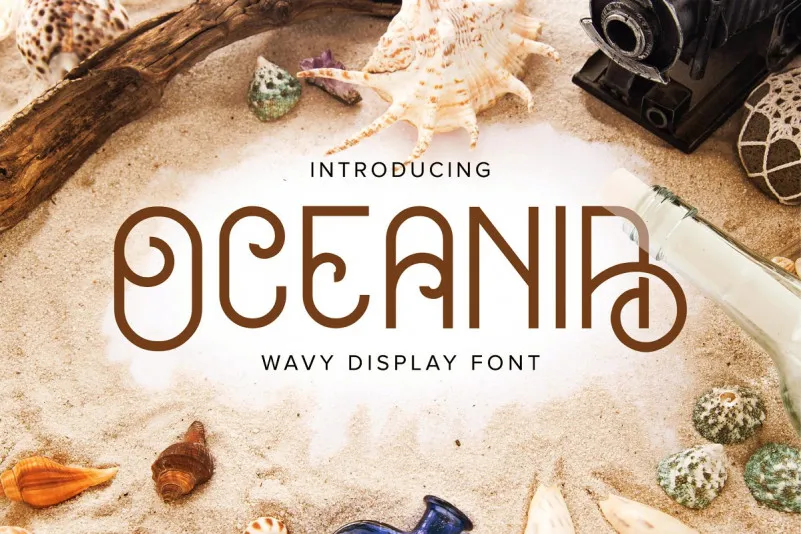
Oceania Display Font – Download Grátis
Descubra Oceania Display Font, uma fonte display icônica criada pela LetterStuff Typefoundry. Esta wavy typeface é perfeita para estilos visuais vibrantes e criativos. Com sua elegante onda doce e suave como o mar tropical, ela destaca-se em qualquer projeto de design. Ideal tanto para headlines quanto para títulos de pôsteres, capas de livros ou mesmo textos neon, logo tipo, camisetas e muito mais. Combine simplicidade com modernidade, Oceania Display Font é a escolha perfeita para aqueles que buscam uma fonte display única e vibrante. Não hesite em explorar sua versatilidade em seu próximo projeto visual.